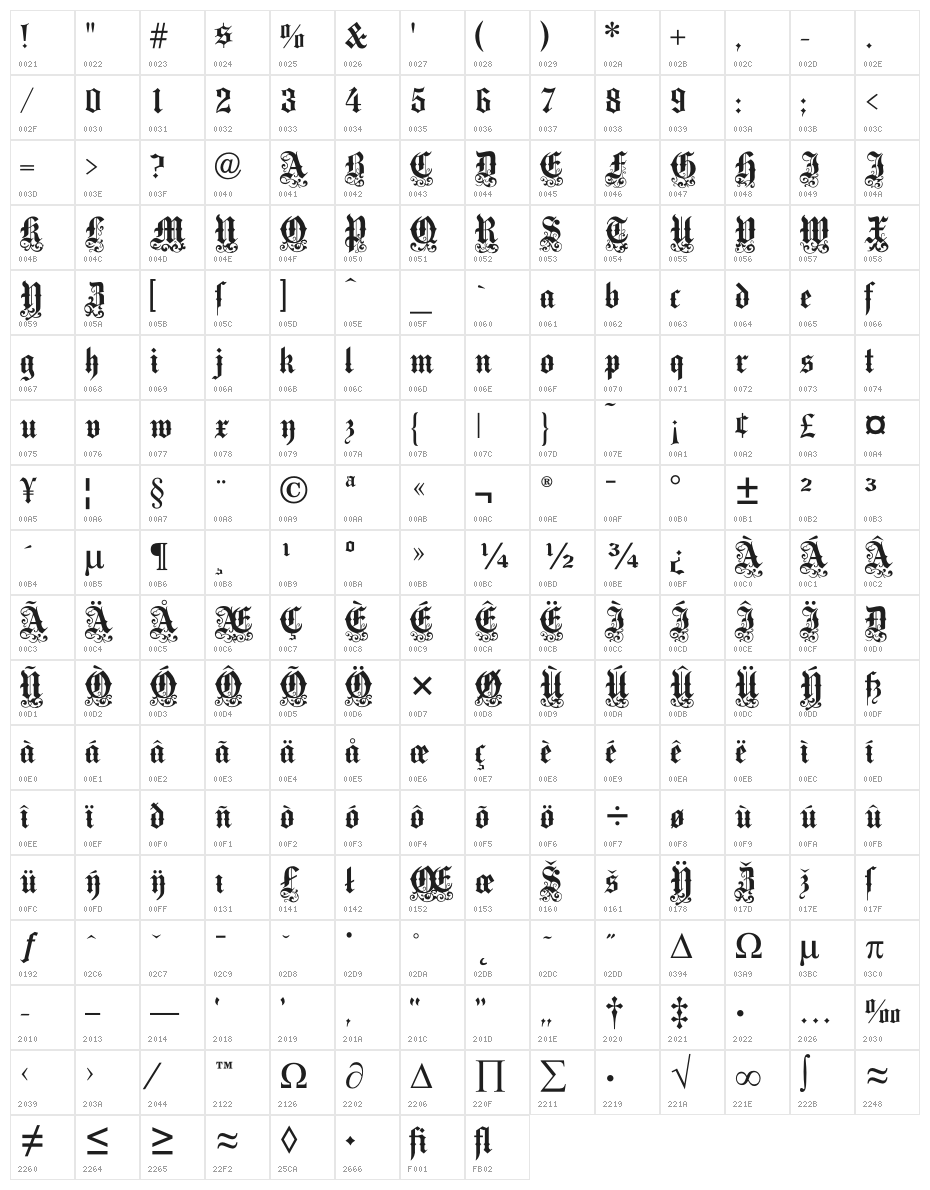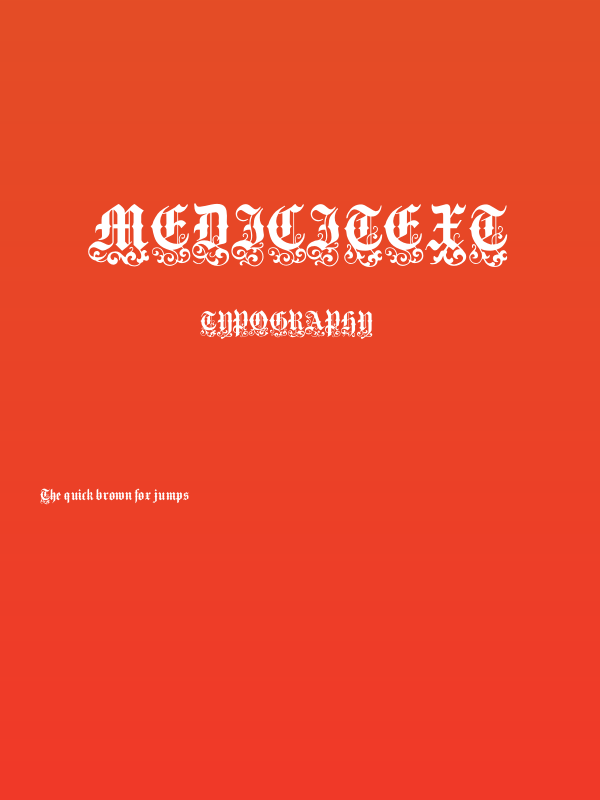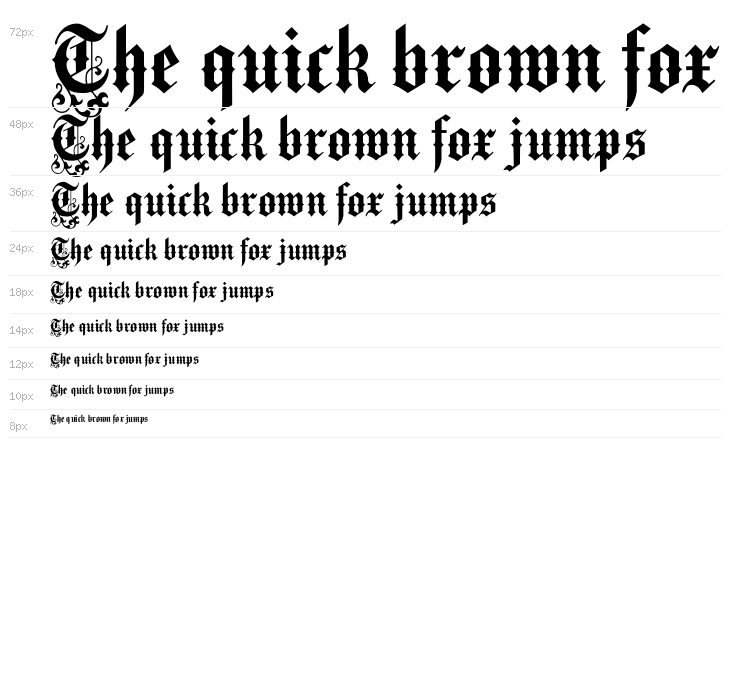
MediciText Font
✎ Gothic
| الفئات | Gothic |
| النمط العام | Vintage |
| حالة الاستخدام | Headlines, Logos, Decorative text |
| مشاريع مقترحة | Ideal for wedding invitations, certificates, historical documents, book covers, and branding that requires a vintage or gothic aesthetic. |